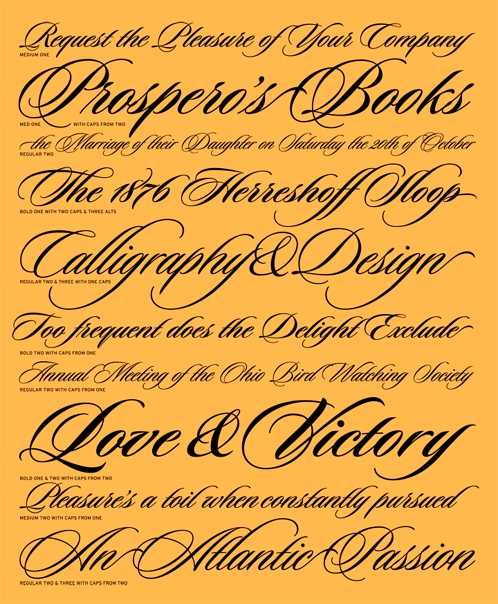
10 самых красивых шрифтов в дизайне
Читая статью в журнале или газете, на что в первую очередь вы обращаете внимание? На каллиграфию, размер букв, их наклон. Неотъемлемой частью успеха любой статьи является её эстетическая составляющая. Ведь читатели любят глазами! Поэтому сегодняшняя статья посвящена самым красивым и популярным шрифтам мира.
Шрифт оказывает значительное влияние на то, как статья или газета принимается аудиторией. Изначально, очень важно правильно расставить акценты в своей публикации и выбрать правильный шрифт. Ведь именно от него зависит успех вашей работы. А теперь представляю вам топ-10 самых красивых шрифтов, по мнению редакторов вашего любимого журнала.
Helvetica Now
Перед вами самый красивый и известный шрифт во всем мире. Он был изобретен швейцарцем Максом Мидингером в 1957 году. Этот шрифт считается стандартным, и применяется во всех сферах уже больше 50-ти лет. Его огромную популярность объясняет его внешний вид, шрифт выглядит: модно, аккуратно, лаконично.
Ведь это то, что нужно!
Georgia
Шрифт Georgia – излюбленный почерк для активных пользователей ПК. Он универсален: подходит для любых текстов и заголовков, его любят использовать как в прессе, так и в веб-дизайне. Этот шрифт привлекает своим красивым курсивом и разнообразными начертаниями. Я думаю, что шрифт Georgia будет радовать работников сети еще долгое время.
Bree
Представляю вам самобытный, абстрактный, полный индивидуальности шрифт Bree. Наверняка, вы слышите о нем впервые, ведь и для меня он стал своего рода открытием. Шрифт идеально подойдет для кричащих заголовков, ведь его очертания непременно заставят читателя остановить свой взгляд именно на вашей статье. Этот новомодный шрифт был создан в паре. Его родители – студенты Жозе Скаглионе и Вероники Буриан. Хотелось бы отметить, что совместная работа у них вышла «на ура».
Brandon Grotesque
Этот достаточно «молодой» шрифт был разработан в 2010 году. Он основан на геометрических формах, здесь же можно отметить отсутствие на нем засечек.
Brandon Grotesque привлекает пользователя своей лаконичностью. В нем есть именно та отличительная элегантность, которая заставит задержать взгляд на каждой букве.
Alternate Gothic
Этот шрифт станет для вас лучшим помощником, если вы просто обожаете кричащие заголовки. Он подходит для тех, кто любит наглые, вызывающие, одним словом, фантастические шрифты. Alternate Gothic прекрасно впишется в любую тематику.
Times New Roman
Вы думали, что я могла забыть об этом легендарном шрифте? Я считаю, что он заслуживает свое место в нашем топе. Times New Roman стал уже чем-то вечным. Вот уже почти 100 лет он остается «на плаву». А в чем же секрет его успеха? Это спокойный, лаконичный, адекватный шрифт. Люди всегда нуждаются в таком общепринятом шрифте, а так как на него всегда есть спрос – его актуальность не потеряется никогда.
Sweet Sans
Особенностью Sweet Sans являются его гравировки без засечек, которые являются прямой отсылкой к канцелярским шрифтам начала 20 века.
Он прост и красив. Шрифт идеально вписывается в современные тенденции. И именно поэтому, занимает заслуженное место в нашем рейтинге.
Ronnia Condensed
Все еще не можете подобрать идеальный шрифт для заголовка? Кажется, мы можем вам помочь. Ronnia Condensed – универсальный шрифт, который полюбился многим. Вы можете увидеть его как в заголовках газет, так и в различных отчетах какого-либо предприятия. Ну разве он не идеален?
Polya
Polya – это уникальный, новый и высокохудожественный экранный шрифт. Он был разработан Эдрианом Коке. Если вам наскучили стандартные шрифты, то вам сюда.
Higher
Этот необыкновенный шрифт был создан Марисой Пассос, дизайнером из Португалии. В этом самобытном шрифте есть всё: отклики ретро, идеальные высокие буквы, отсутствие засечек. Вы определенно можете использовать его для своих дизайнерских проектов.
Шрифт – это часть вашего стиля. Всегда нужно делать долгий и кропотливый выбор, ведь залогом успеха является читабельность и эстетичный вид выбранного шрифта.
Как говорится, встречают по одежке. Обрамляйте свои работы лучшими материалами. Запомни, все зависит от притягательности. Надеюсь, что подборка поможет вам в выборе шрифтов. А какой стиль предпочитаете вы